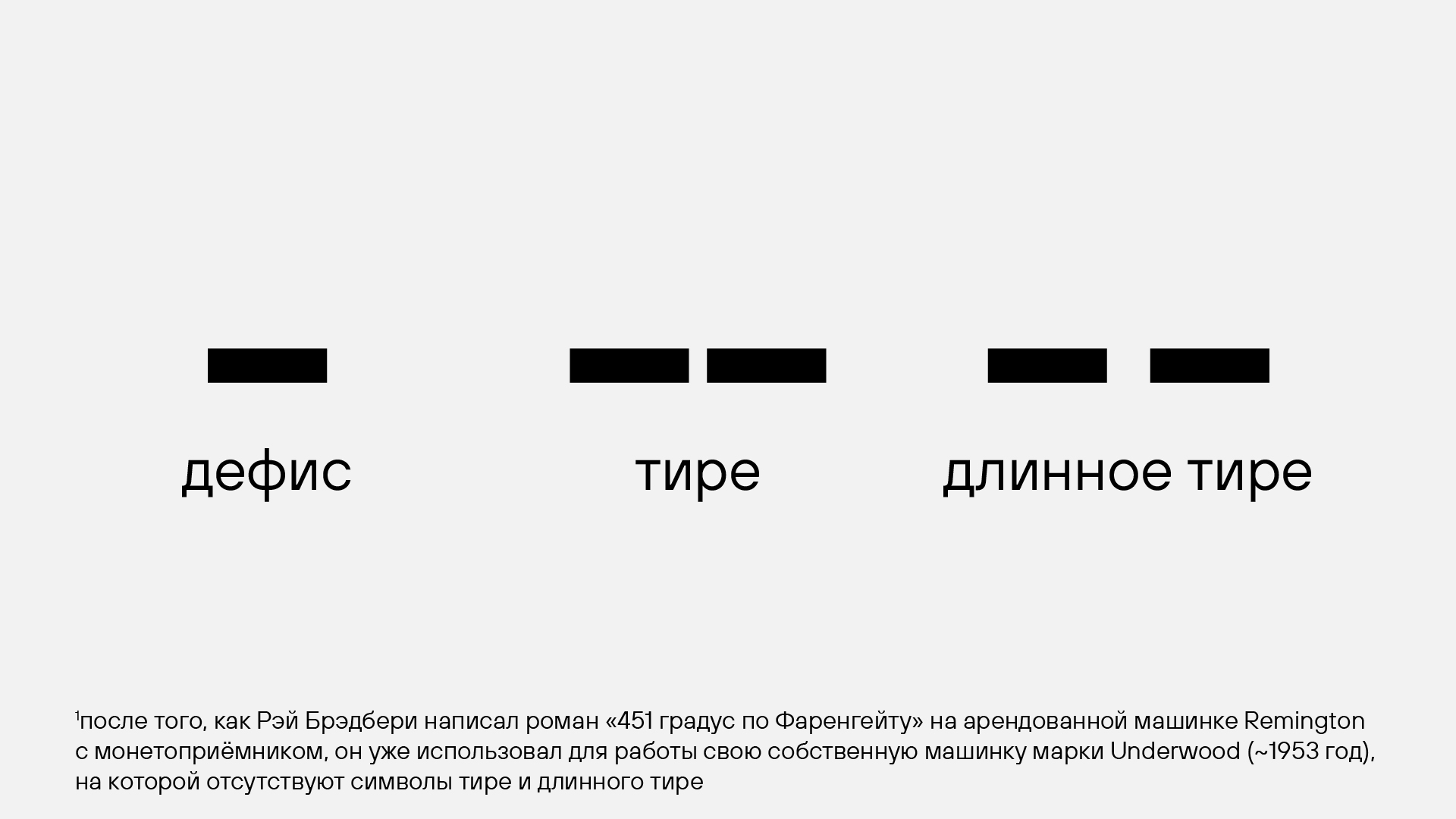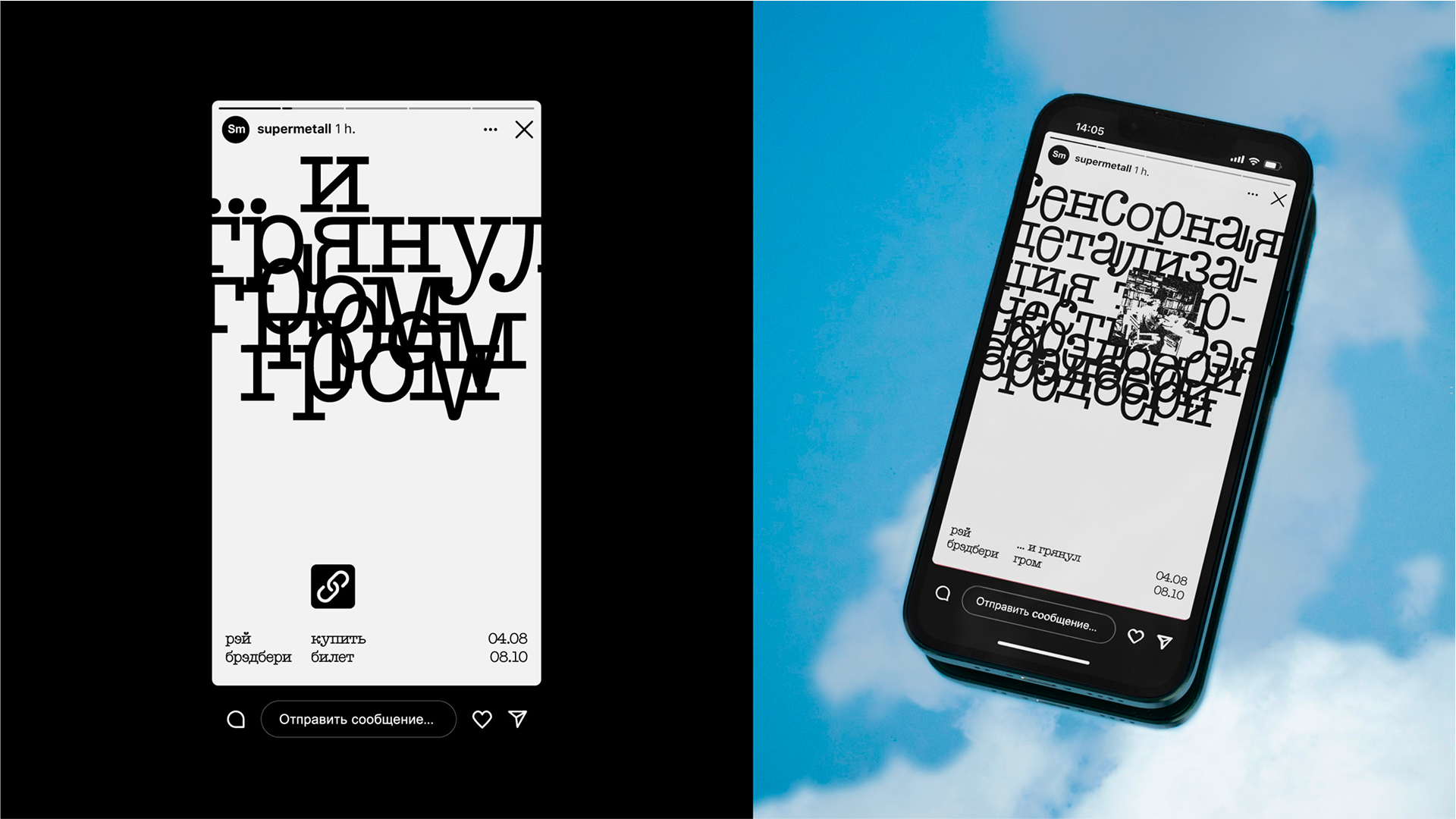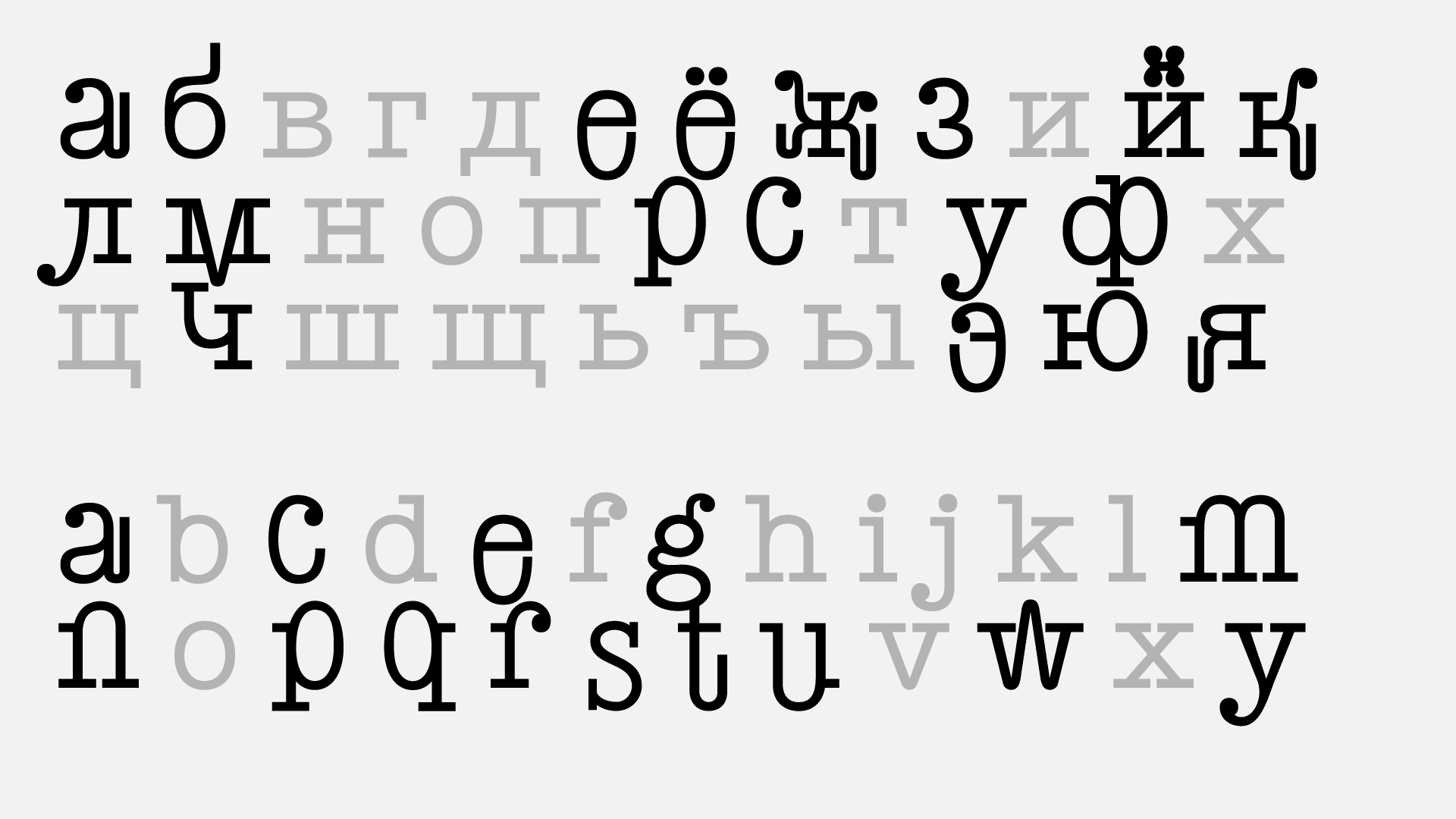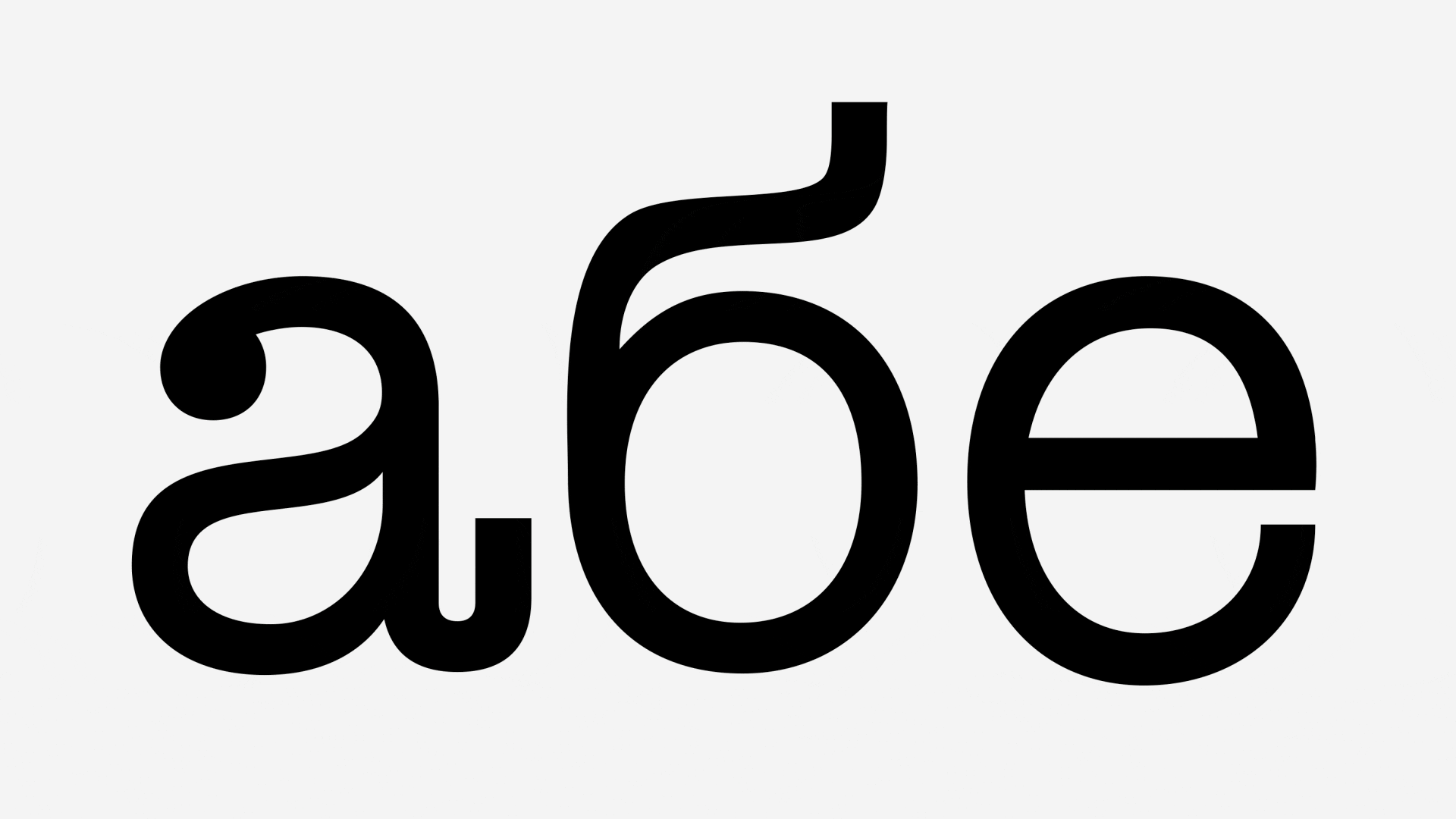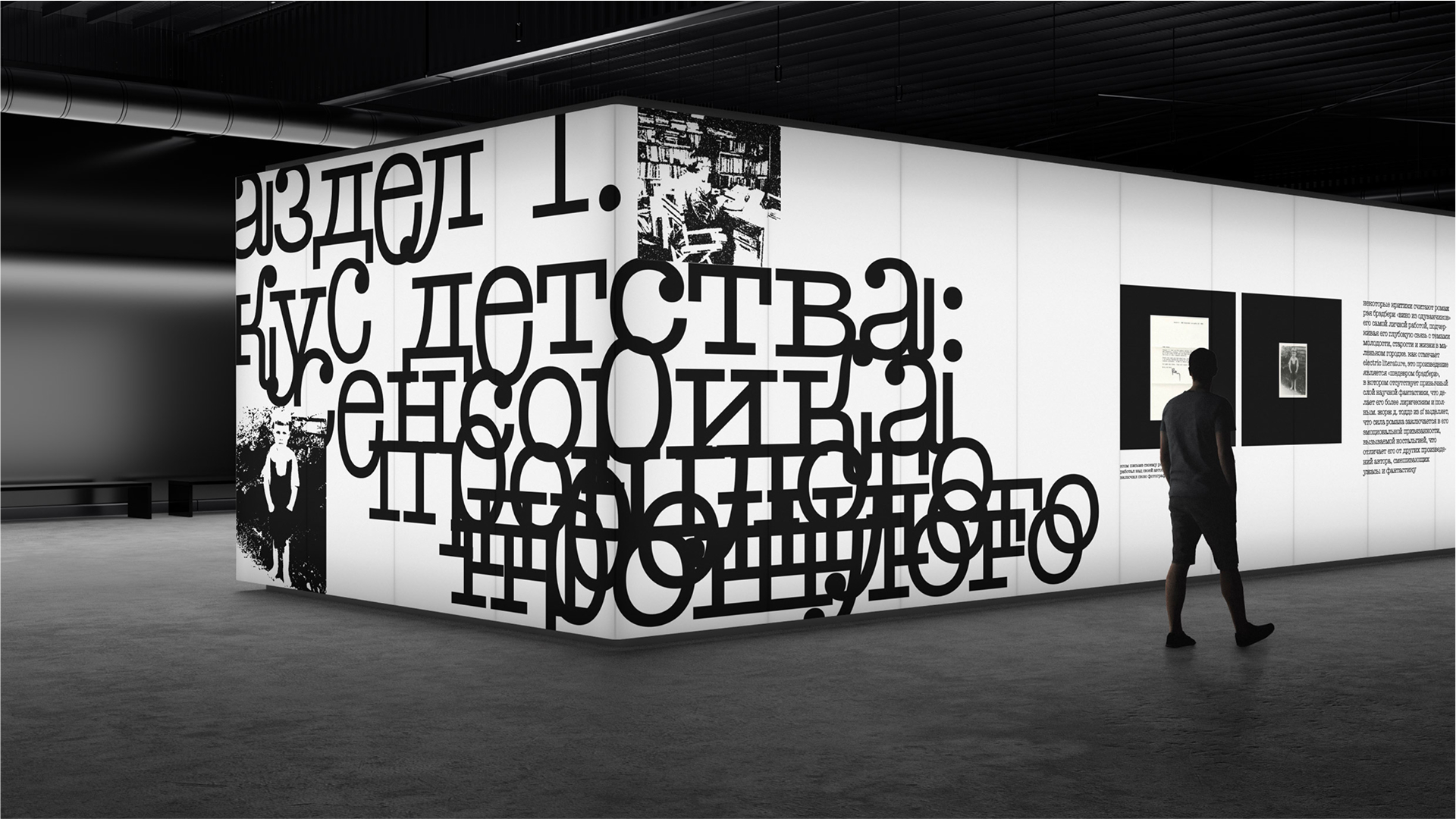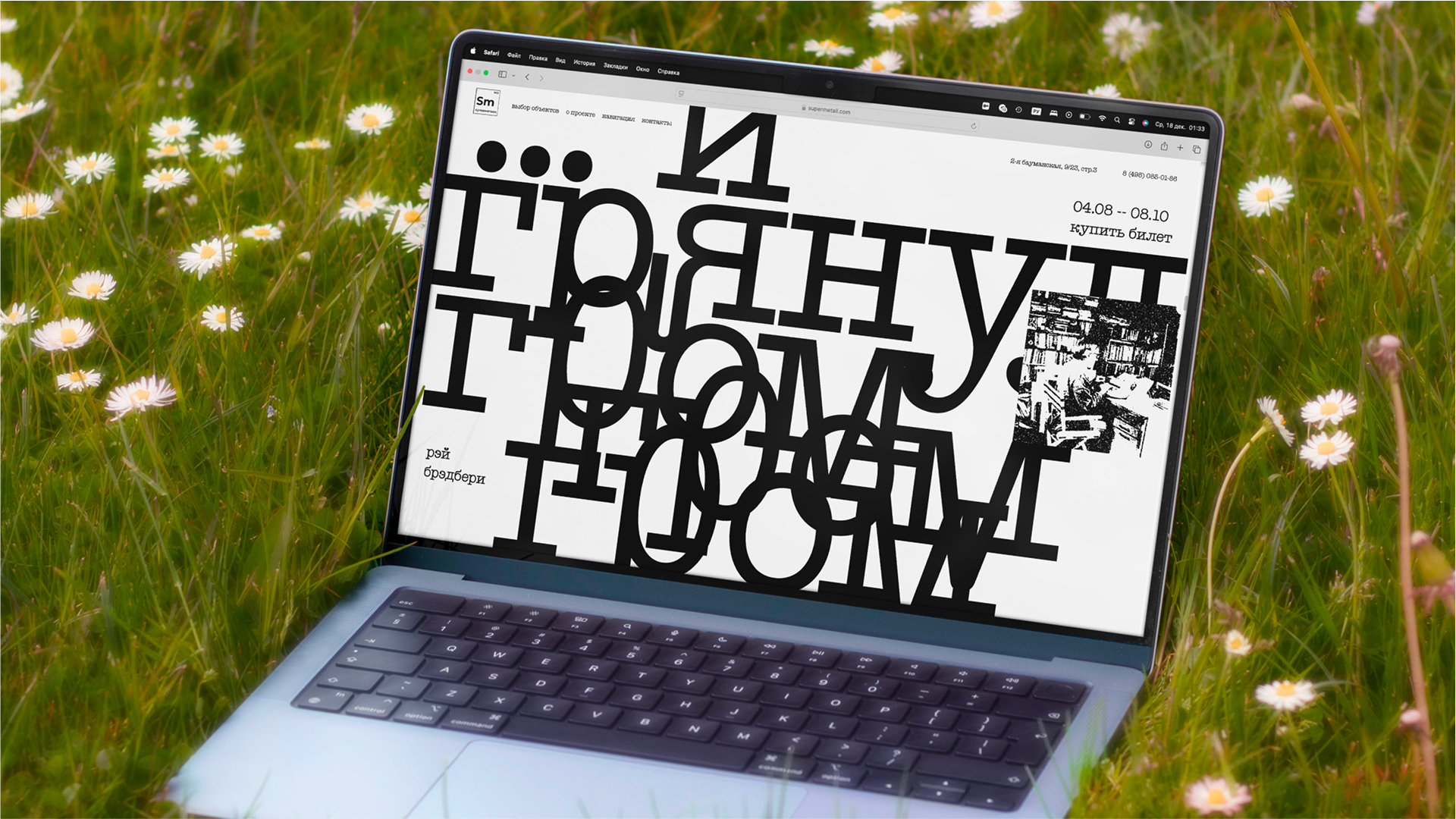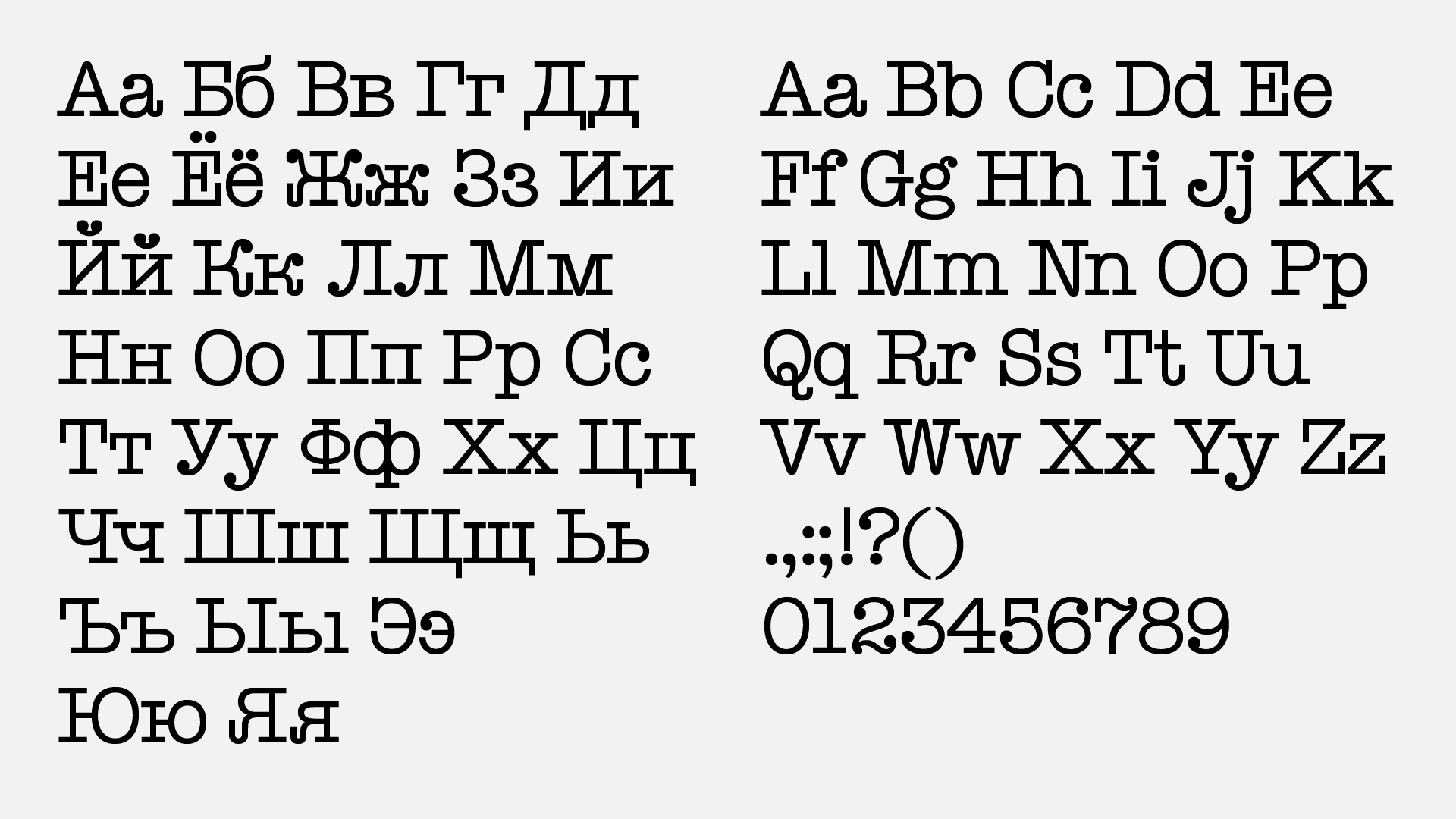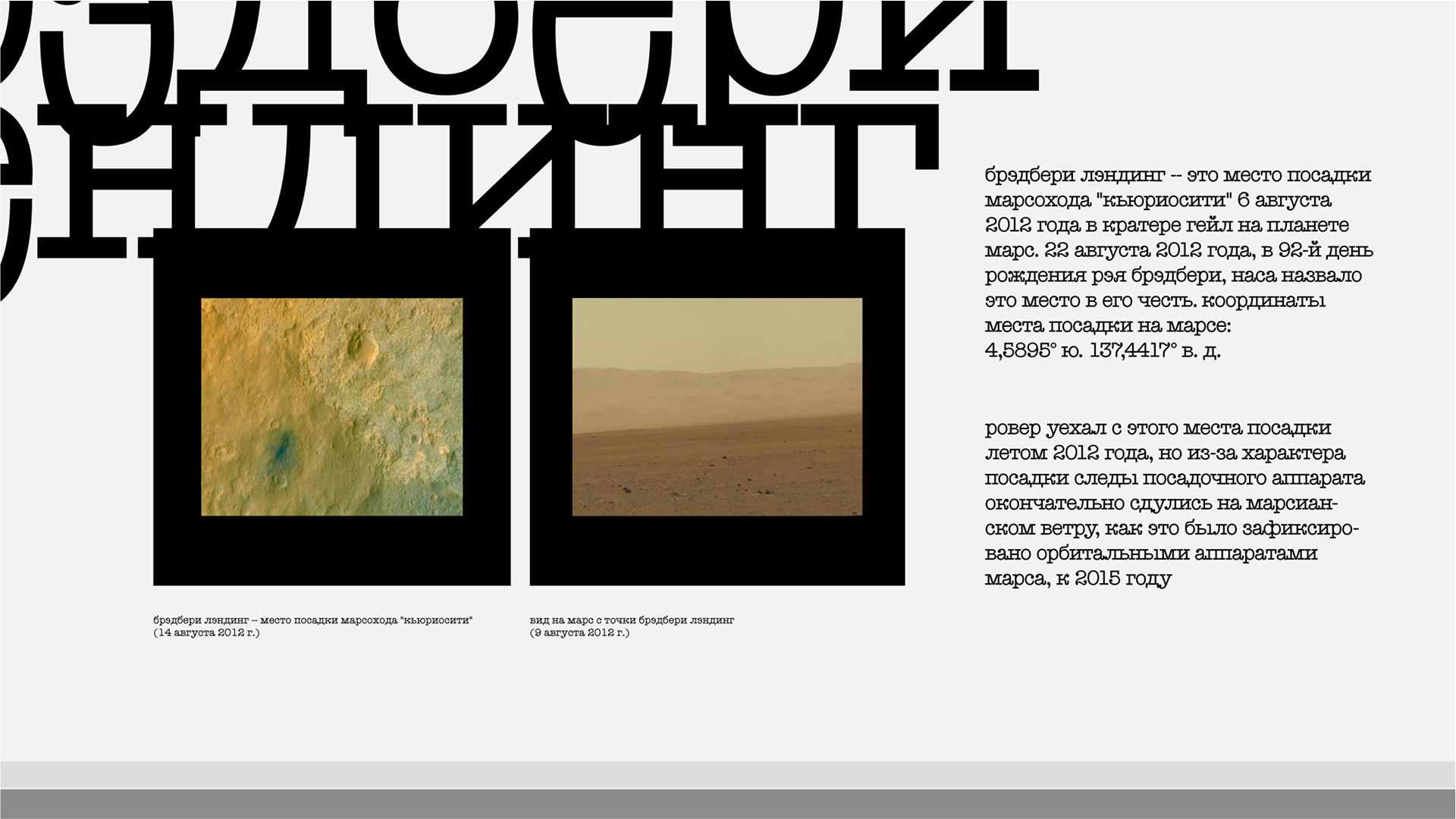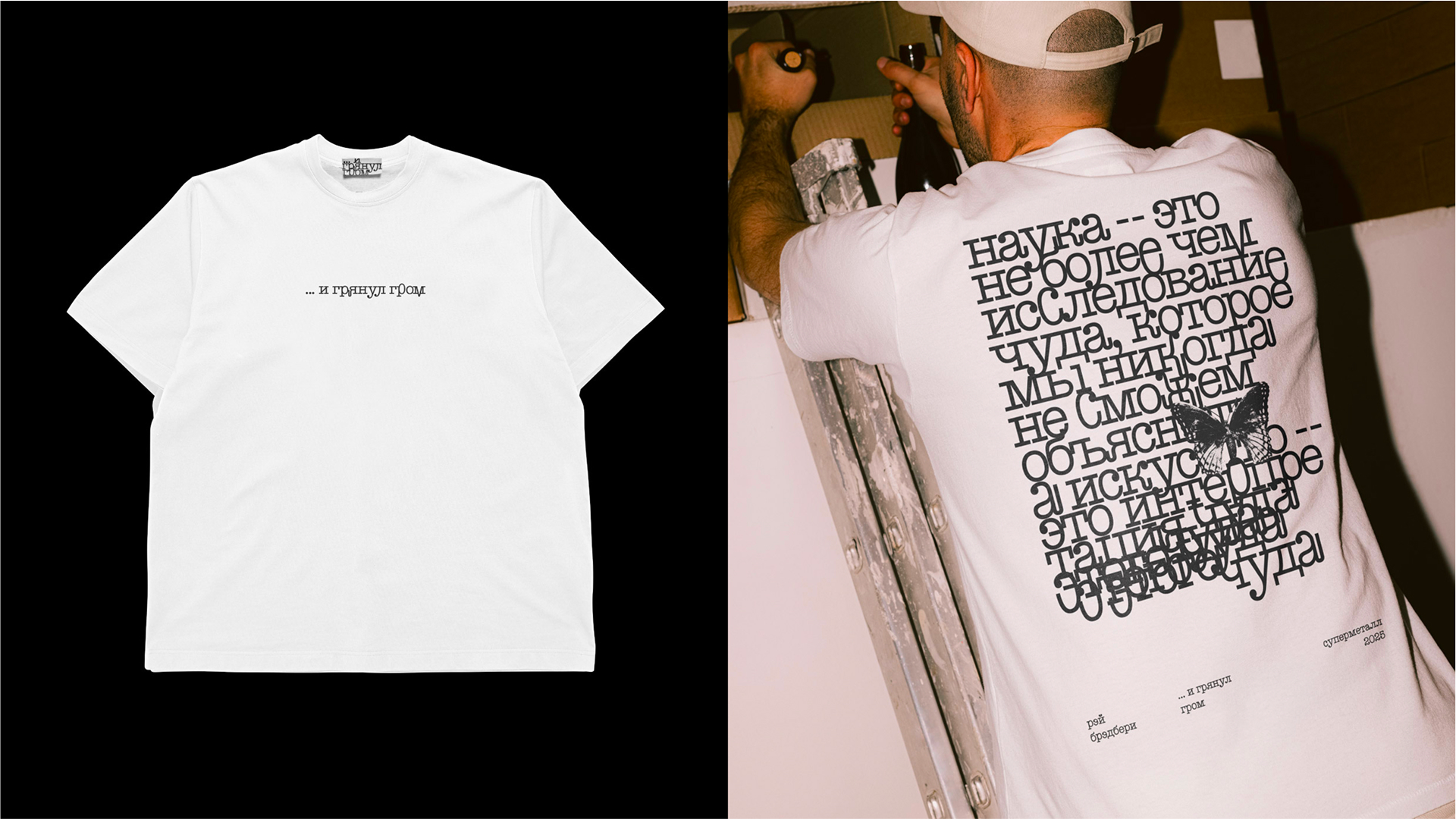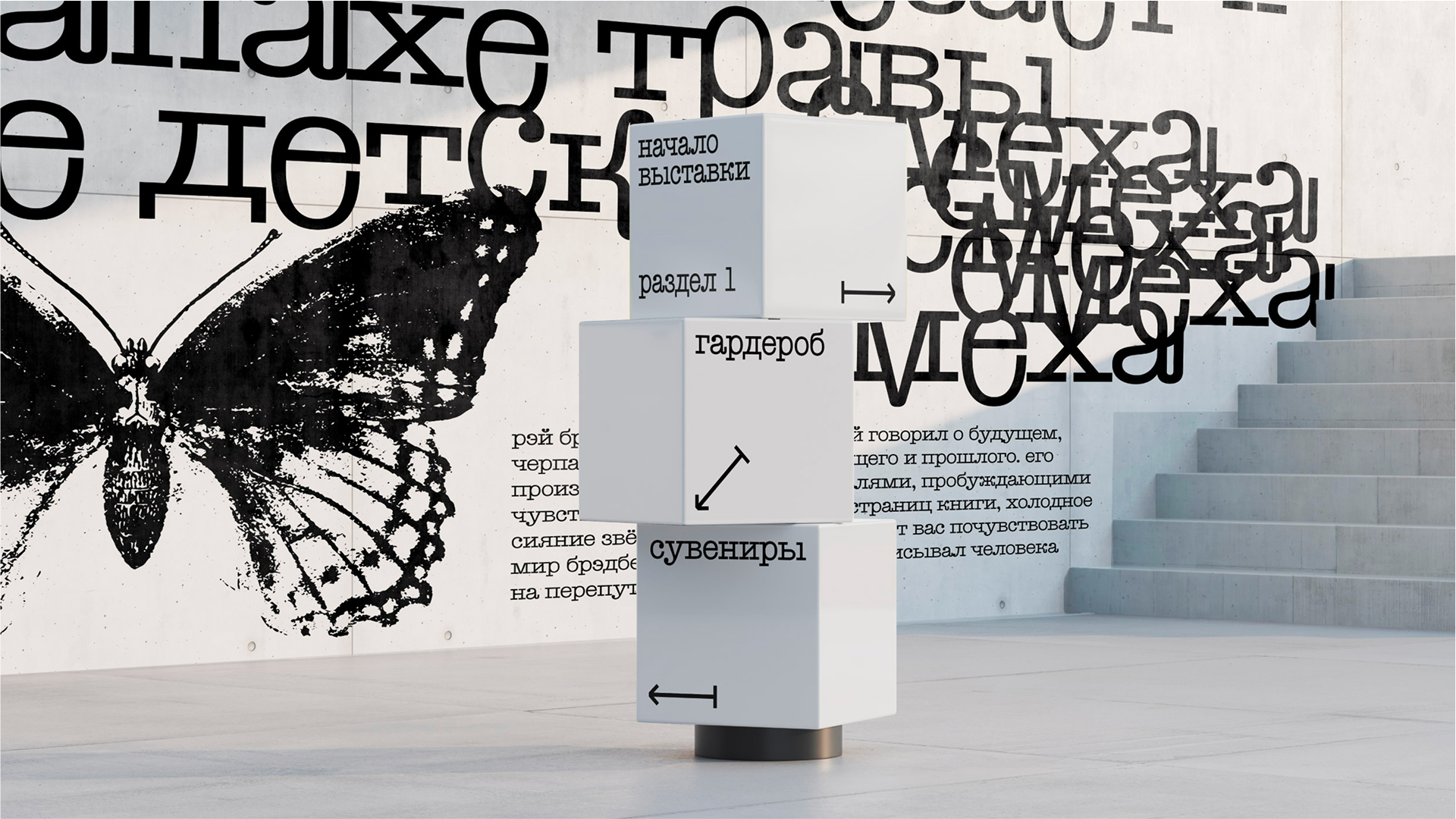
Тиражный шрифт
Ray
Ray — гротескный тайпрайтер с набором альтернатив, отражающих концепцию фантастической пишущей машинки.
Рэй Брэдбери не воспринимал пишущую машинку просто как техническое устройство, для него она была важной частью творческого процесса, источником ощущений и вдохновения. Регулярно он говорил о том, что за клавиатурой нельзя мыслить холодным умом, нужно чувствовать — именно чувства играют главную роль в создании настоящего искусства.
Именно это чудо чувства и превращения было в основе при создании данного шрифта. Тихое и немного пугающее, как и произведения Брэдбери, которые завораживают своим фантастическим реализмом.